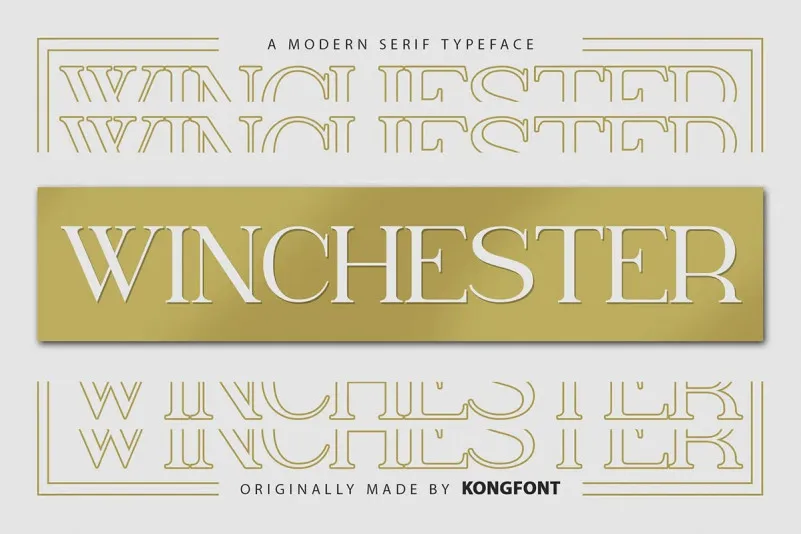
Winchester Font – Fonte Grátis
Winchester Font
A Winchester Font é uma elegante fonte serif produzida pela Kong Font. Ela oferece um toque moderno ao mesmo tempo que preserva a sofisticação dos traços serifados, adaptando-se perfeitamente para diversos usos gráficos. Esta fonte contém todos os elementos básicos com caracteres não-ortográficos, tornando-a uma escolha ideal tanto para uso em letras de estilo script ou assinatura quanto para escrita manual. Ela é especialmente atraente quando combinada com estilos de texto mais delicados, e combina perfeitamente tanto para headlines e títulos quanto para layouts de publicações, logotipos, anúncios, fitas posteriores, citações, design web e embalagens. Com seu charme e versatilidade, a Winchester Font se destaca como uma opção perfeita para designers que buscam um estilo sofisticado e moderno. É ótima para uso em publicações de revista, branding, embalagens ou até mesmo em livros e materiais de viagem. Seu design elegante permite harmonizar com diversos estilos de criação, tornando-a uma escolha inteligente para um leque amplo de projetos criativos.